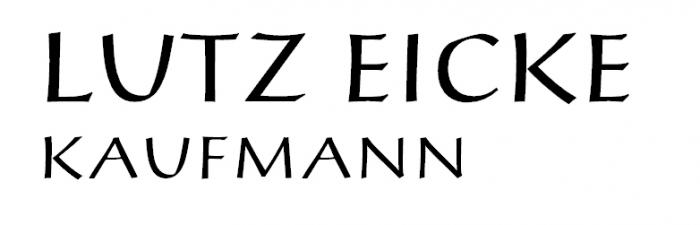
mindestens 40 Jahre alt
ich habe vor mindestens 40 Jahren einen Briefbogen drucken lassen mit dieser Schrift.
Sie wurde damals von Anwaltskanzleien verwendet und auch als Beschriftung von Tafeln von Justizgebäuden.
Die Identifikation über Acrobat hat nicht funktioniert; es wurde "Constantina" angegeben.